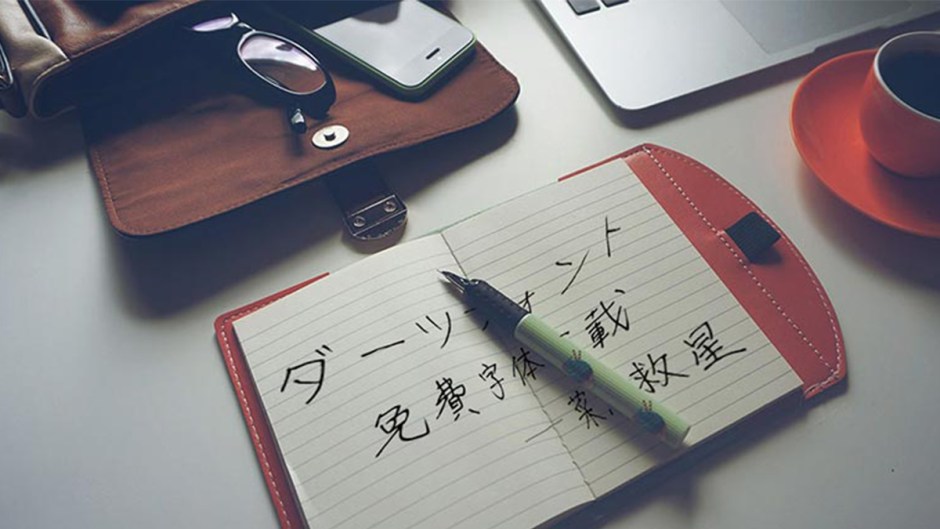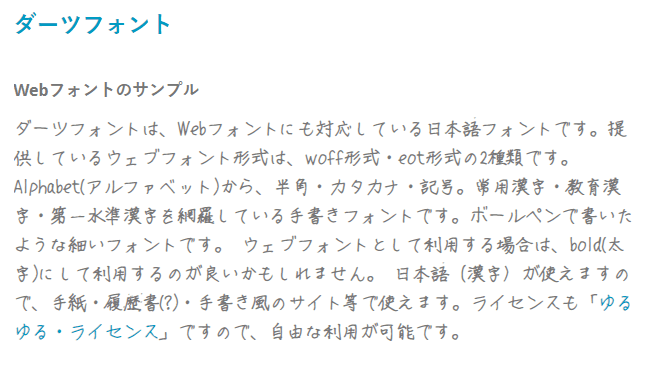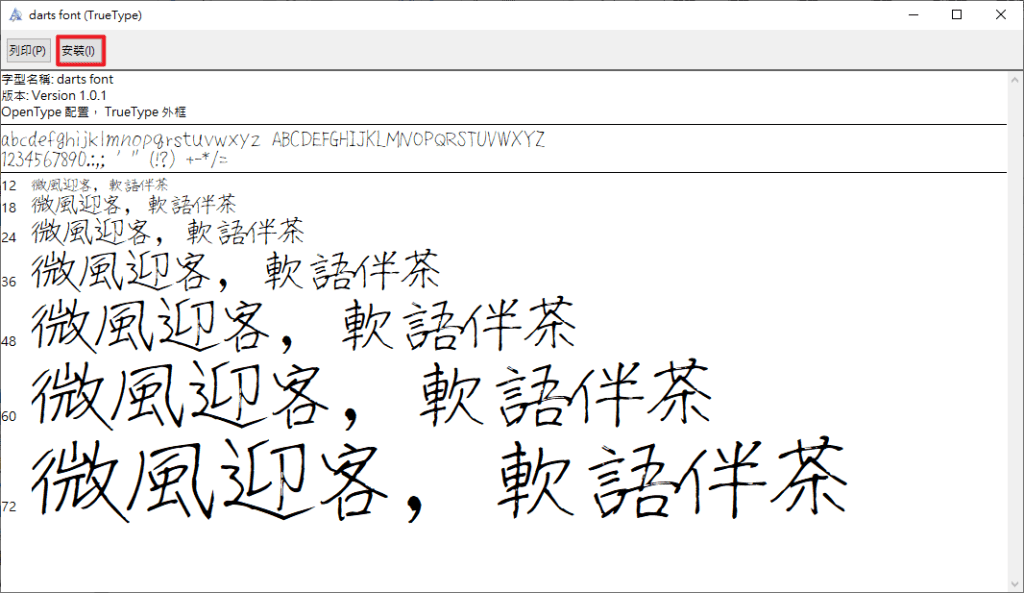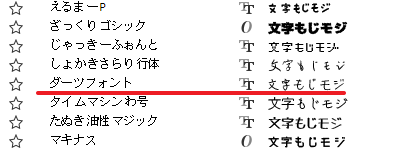
聯成電腦分享:免費字體下載-ダーツフォント 發佈日期: 2021-02-242021-02-23 作者: Natty 文、菜鳥編 手繪風的字體相當多,小編印象中也分享了不少。不過這次的字體有讓我感覺很貼近真實手寫,沒有過多的字體修飾,可能有些字體你還最覺得不是美觀但又有特色,喜歡手寫風的可以體驗看看。 字體名稱:ダーツフォント下載位置:http://fontfree.me/1665 小編一開始看到字體的呈現時,並沒有馬上吸引到我,不過在多看幾次又覺得挺有特色的。 在網站上就標示字體可商用 點擊按鈕開啟下載網頁 字體也支援Web,所以你可以在網站上馬上就看到字體的應用。 下圖標示可開啟字體授權聲明網頁,所以使用前最好先了解一下。 從更新紀錄來看,是一款還有在維護中的字體。 點擊標示處下載字體 解壓縮後,可以看到五個檔案,文字檔是說明文件,另外還有三個Web字體。 開啟字體檔安裝 一樣的,字體在Adobe中與Office中名稱不同。Adobe: Office: 免費字體為網路搜尋而來,使用權限請以官方文件與說明為主 加入菜鳥救星官方Line並回覆「我想看文章」,不定期獲得更多知識吧! 不同頻道,不同知識! Facebook Instagram Youtube 分享此文: 分享到 X(在新視窗中開啟) X 分享到 Facebook(在新視窗中開啟) Facebook 分享到 Telegram(在新視窗中開啟) Telegram 以電子郵件將連結傳送給朋友(在新視窗中開啟) 電子郵件 請按讚:喜歡 正在載入... 相關